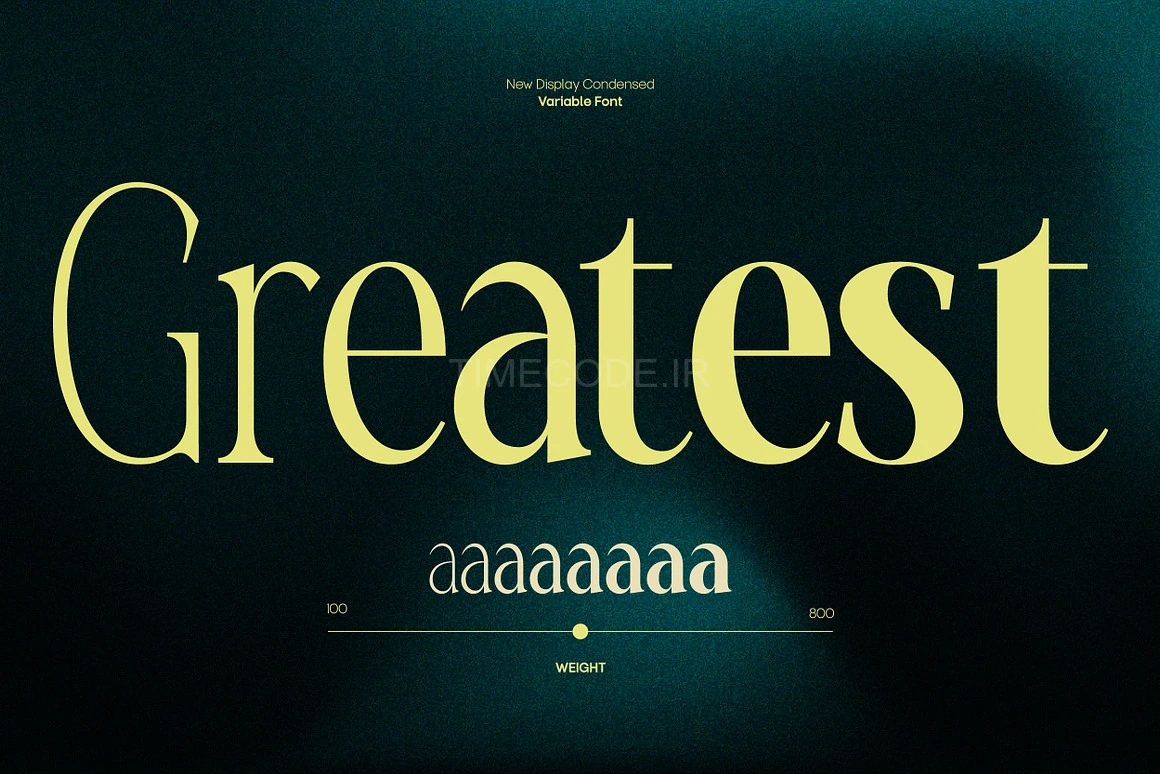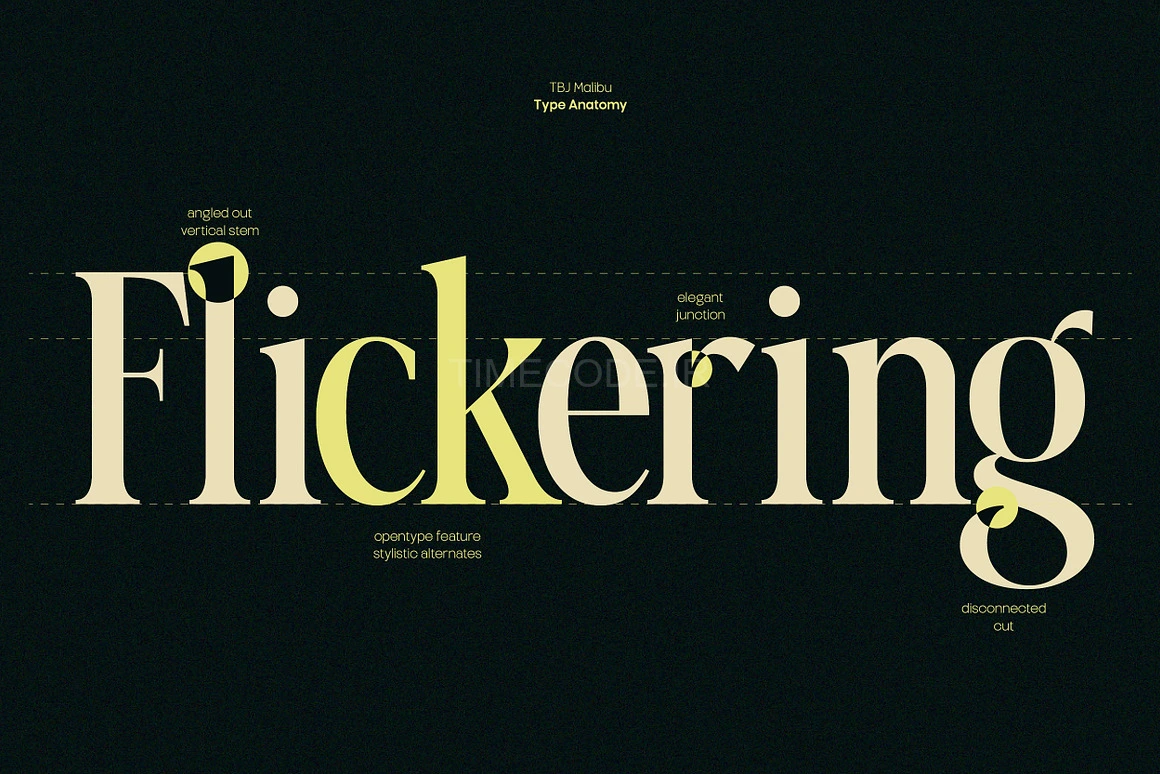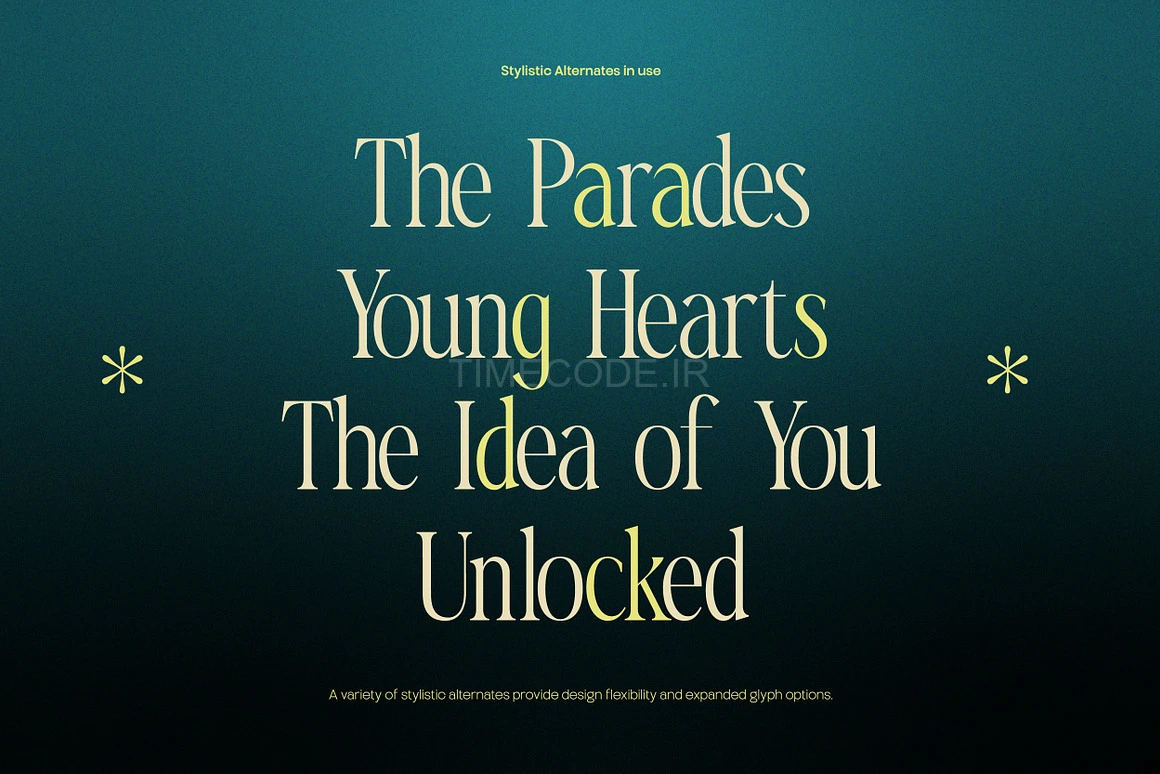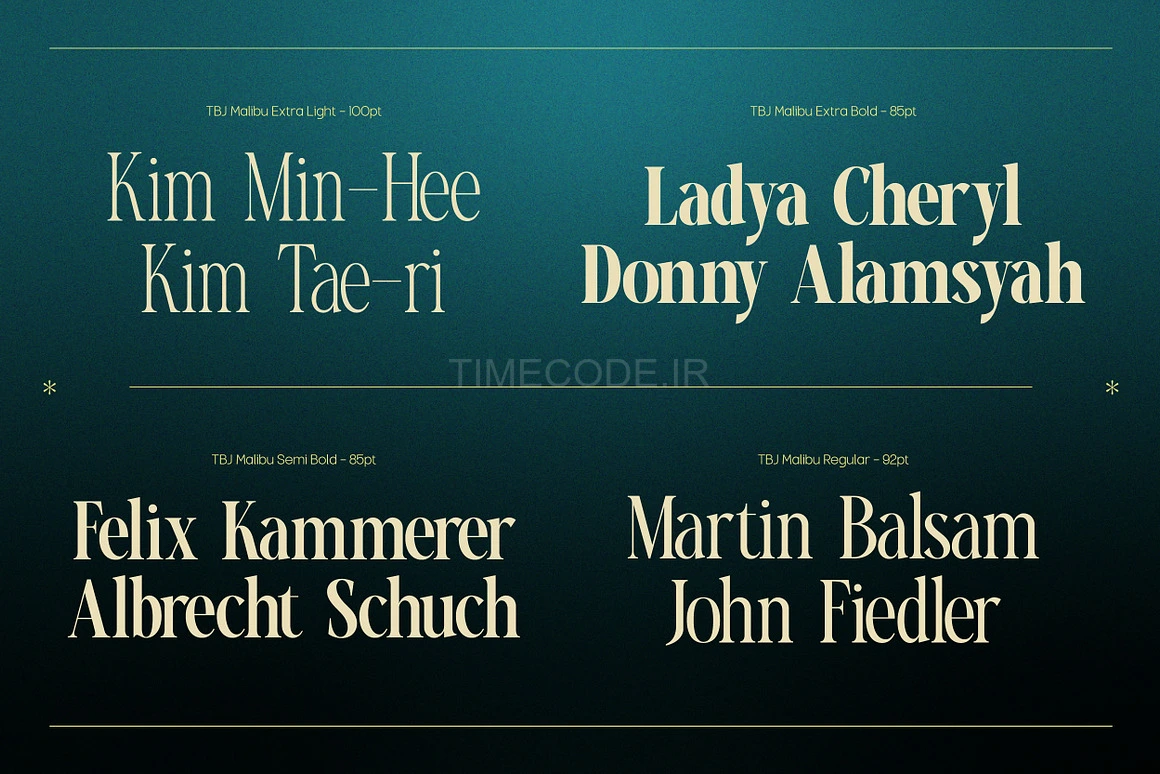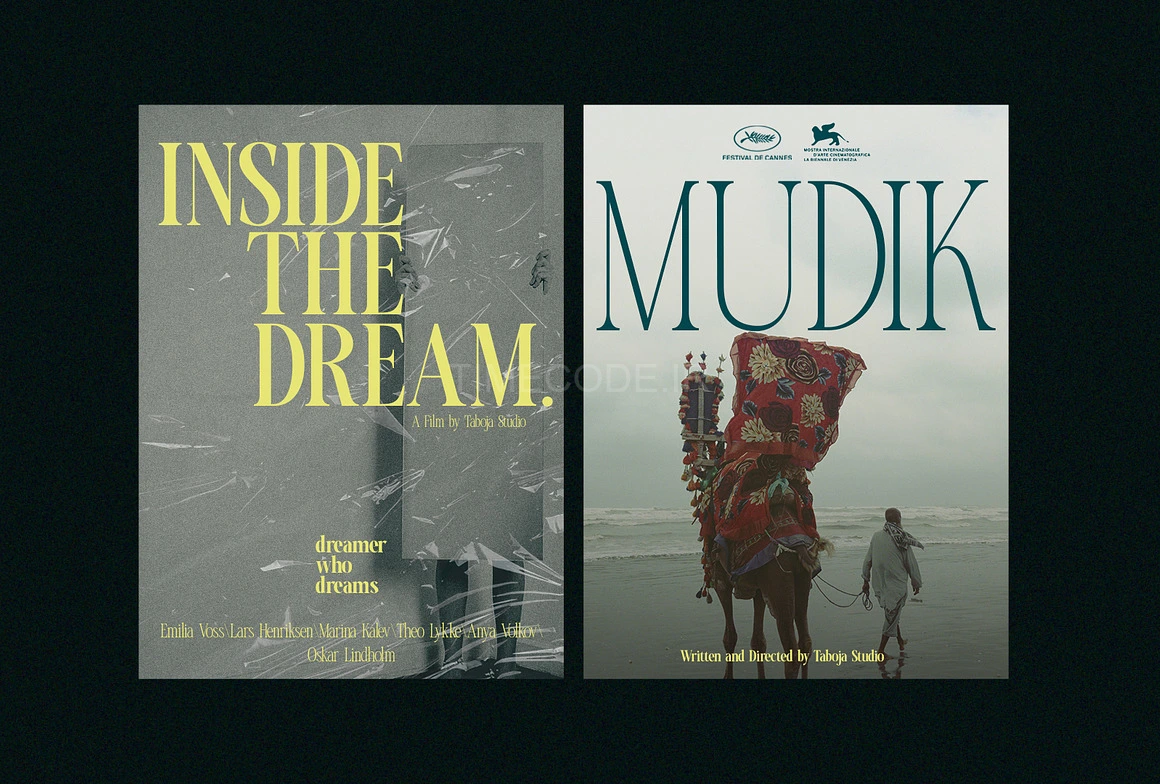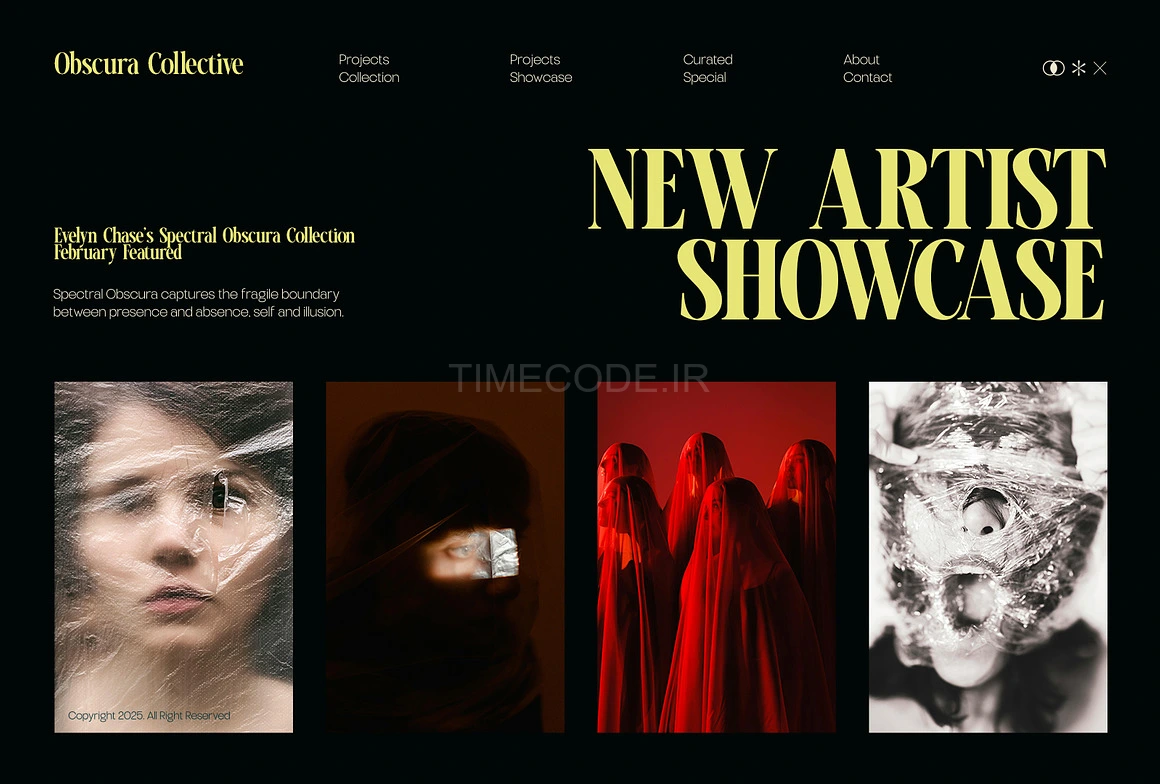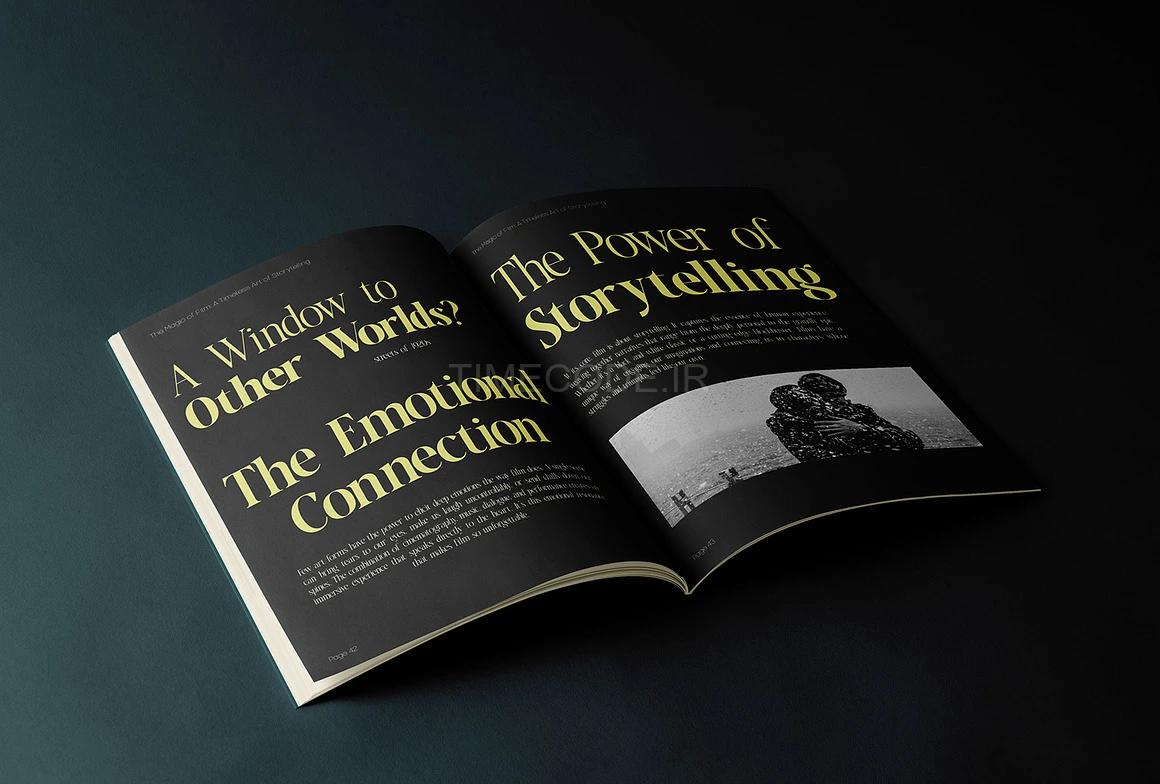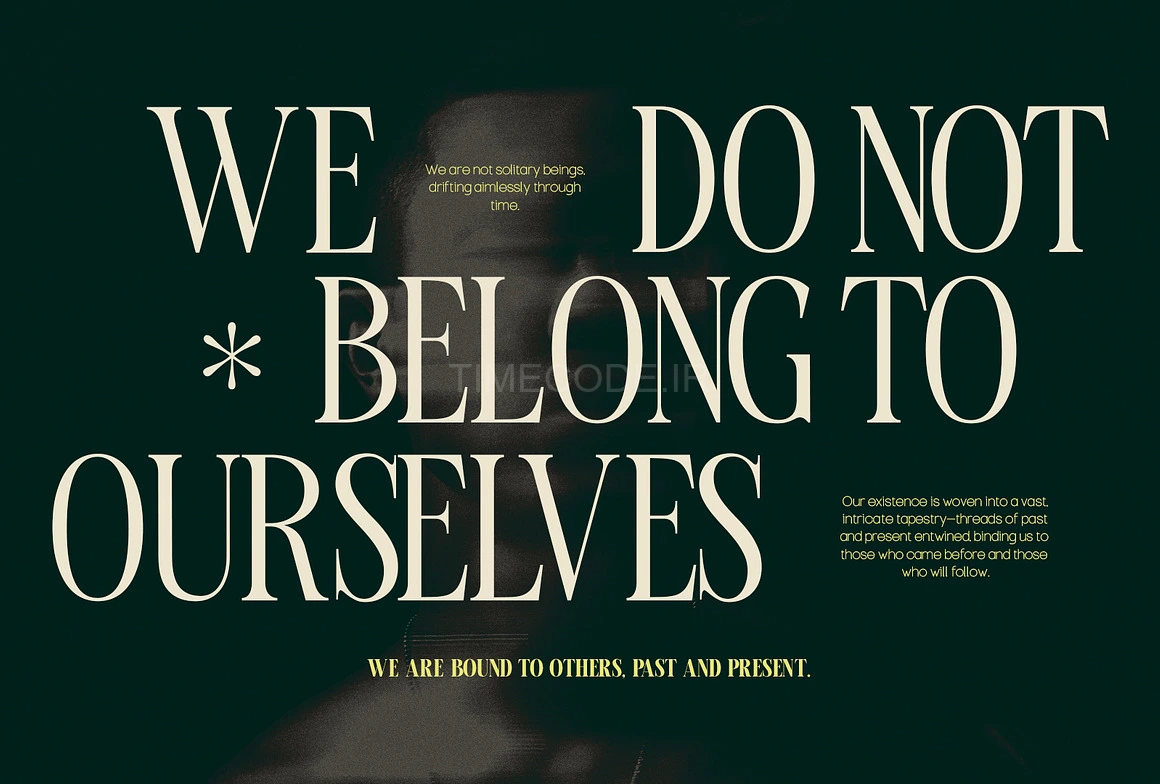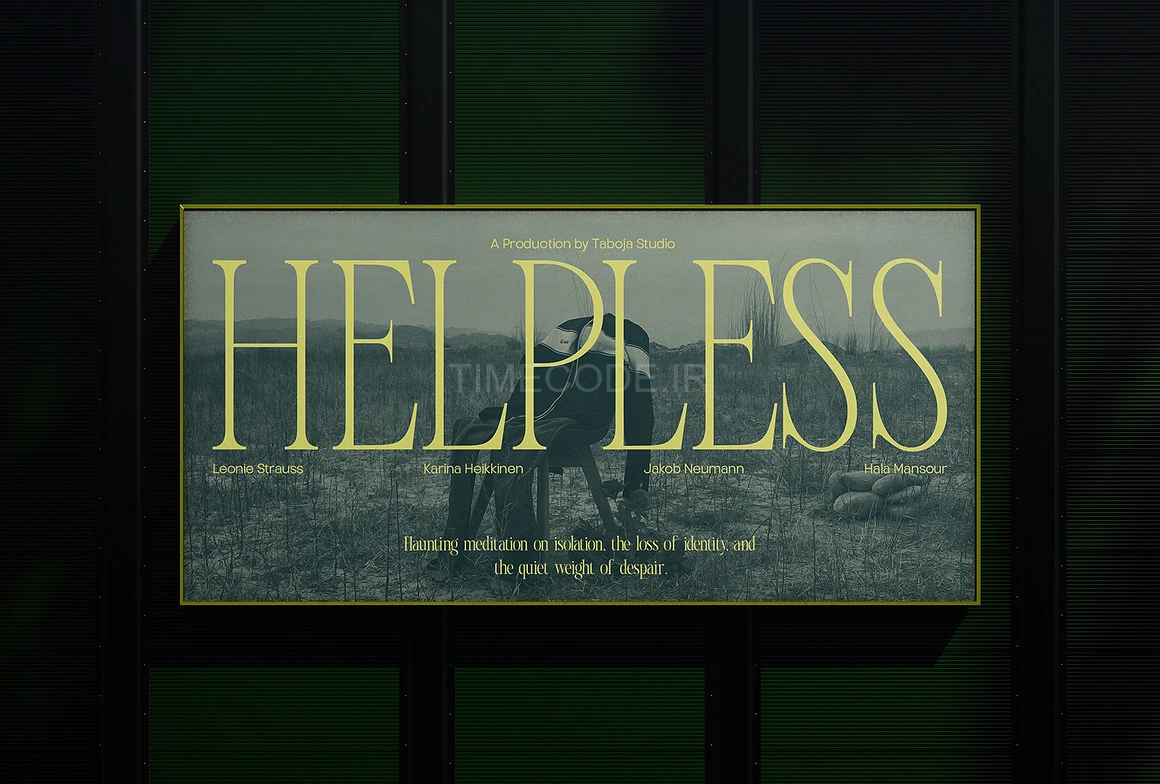
• فونت انگلیسی مدرن باریک
• TBJ Malibu Condensed Display Font
فونت انگلیسی مدرن باریک
“TBJ Malibu” یک فونت نمایشگر خیره‌کننده با سبک فشرده (Condensed) و قابلیت فونت متغیر (Variable Font) است که توسط Taboja.studio تولید شده تا استانداردی جدید را در دنیای تایپوگرافی نمایشگر تعریف کند. این فونت نه تنها ظاهری ظریف با نسبت‌های باریک و بلند ارائه می‌دهد، بلکه با ۸ نوع فونت متغیر خود، انعطاف‌پذیری فوق‌العاده‌ای را فراهم می‌کند.
هر نوع متغیر امکان تنظیم عرض و وزن را فراهم می‌کند و به طراحان اجازه می‌دهد ترکیباتی را ایجاد کنند که واقعاً متناسب با نیازهایشان باشد – از تایپوگرافی سبک‌تر و ظریف‌تر گرفته تا نسخه‌های دراماتیک‌تر و پررنگ‌تر برای برندینگ، لوگوها، سرمقاله‌ها و سایر پروژه‌های خلاقانه بی‌نقص است.
“TBJ Malibu” تنها یک فونت نیست، بلکه ابزاری انعطاف‌پذیر و شخصیت‌مند برای بیان بصری است که برای ایجاد حسی منحصر به فرد و معاصر در طیف گسترده‌ای از کاربردهای طراحی، طراحی شده است.
“TBJ Malibu ” is a stunning display font with Condensed style and Variable Font capability, produced by Taboja.studio to set a new standard in the world of display typography. This font not only offers an elegant look with slim and tall proportions, but also provides tremendous flexibility with its 8 variable font variants.
Each variant allows for width and weight adjustments, allowing designers to create compositions that truly fit their needs-from lighter, subtle typography, to more dramatic bold versions. The elegant green-blue graded background further strengthens the visual appeal of this font, showcasing its aesthetic potential that is perfect for branding, logos, editorials and other creative projects.
“TBJ Malibu ” is not just a font, but a flexible and characterful visual expression tool, designed to give an exclusive and contemporary feel in a wide range of design applications.